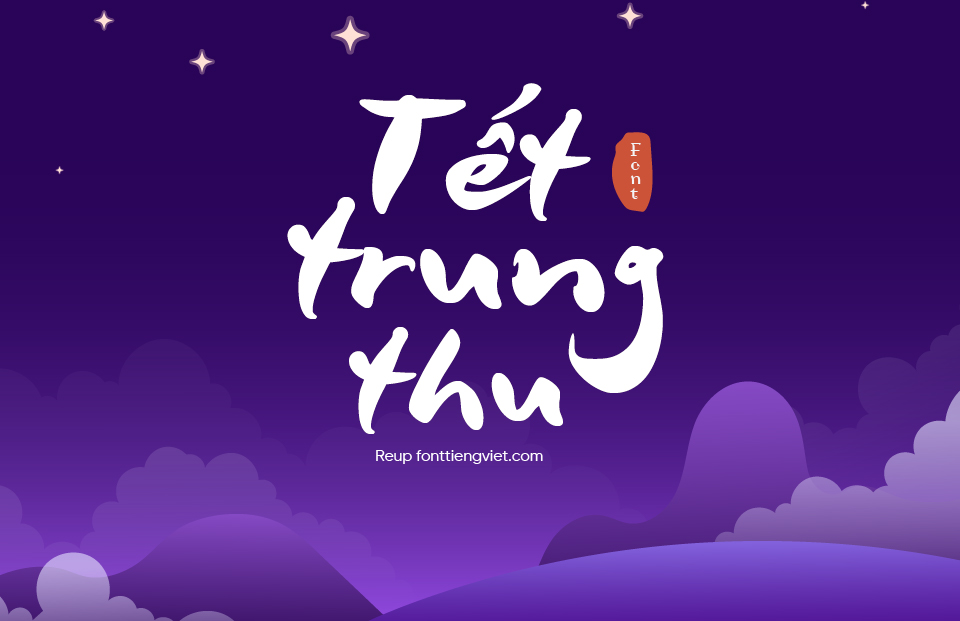
Font Việt hóa LNTH DeBorstel Brush – Font trung thu – Nét bút phá cách cho mùa lễ hội
Trong thiết kế đồ họa, việc lựa chọn một Font Chữ phù hợp là yếu tố quyết định tính thẩm mỹ của tác phẩm. Font Việt hóa LNTH DeBorstel Brush – Font trung thu nổi lên như một lựa chọn hoàn hảo cho các dự án sáng tạo vào dịp Tết Đoàn viên. Với những đường nét mô phỏng nét cọ vẽ tay mạnh mẽ, bộ phông này mang lại cảm giác mộc mạc nhưng không kém phần hiện đại, giúp thông điệp của bạn trở nên nổi bật và thu hút ánh nhìn ngay từ lần đầu tiên.
Đặc điểm nổi bật của Font Việt hóa LNTH DeBorstel Brush – Font trung thu
Bộ font này sở hữu phong cách brush đặc trưng với các nét xước tự nhiên, tạo nên hiệu ứng thị giác đầy tính nghệ thuật. Được tối ưu hóa hoàn toàn cho tiếng Việt, bạn có thể yên tâm sử dụng mà không lo lỗi hiển thị dấu câu. Đây là công cụ hỗ trợ đắc lực cho các bạn học sinh trong việc thiết kế thiệp chúc mừng, báo tường hay trang trí gian hàng trung thu tại trường học.
Ứng dụng linh hoạt trong thiết kế giáo dục
Nhờ vẻ ngoài năng động, Font Việt hóa LNTH DeBorstel Brush – Font trung thu cực kỳ phù hợp để làm tiêu đề cho các áp phích sự kiện, bìa sách hoặc các slide thuyết trình cần sự phá cách. Các giáo viên cũng có thể sử dụng bộ phông này để tạo ra những học liệu sinh động, giúp học sinh hào hứng hơn với các hoạt động truyền thống của dân tộc.